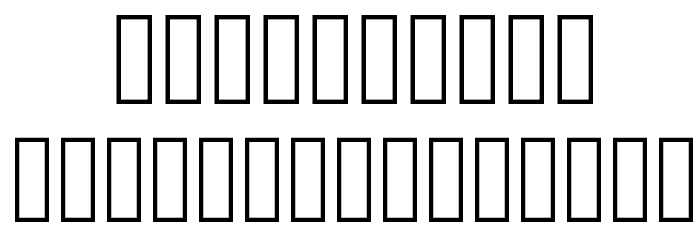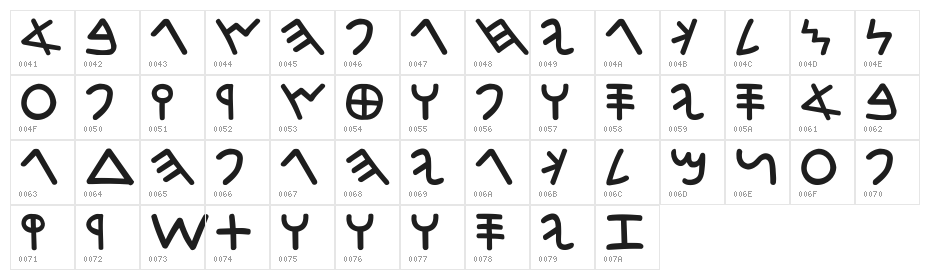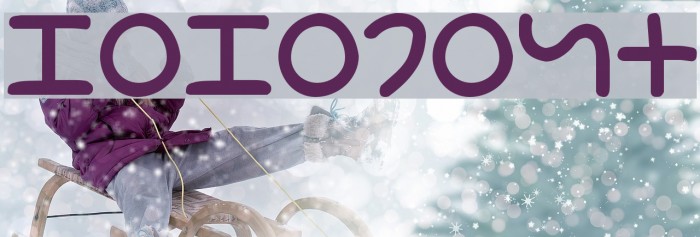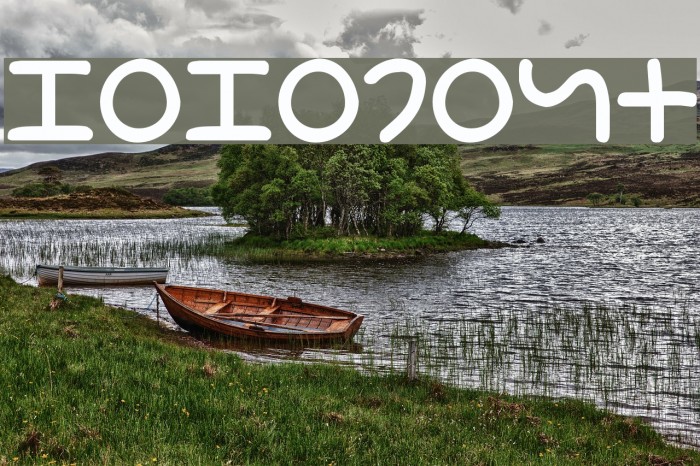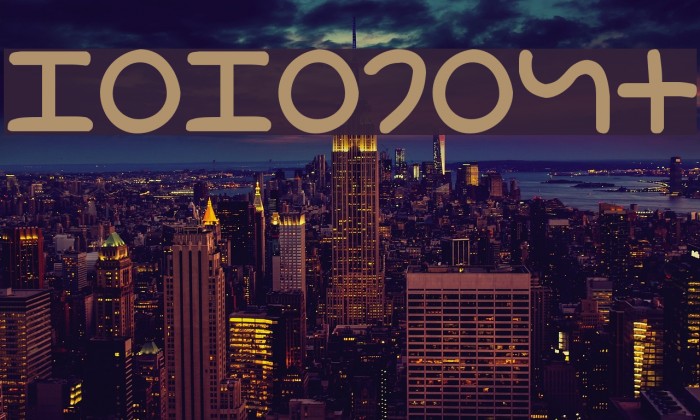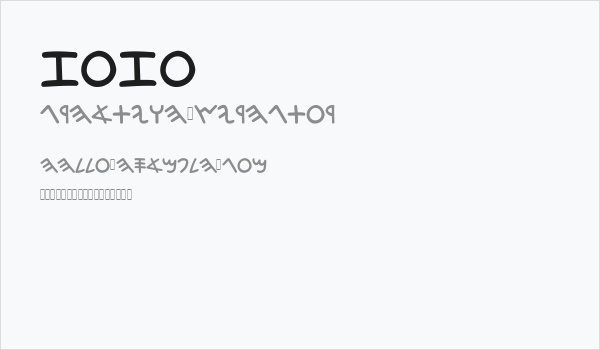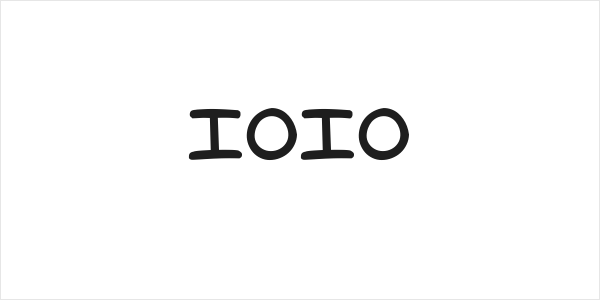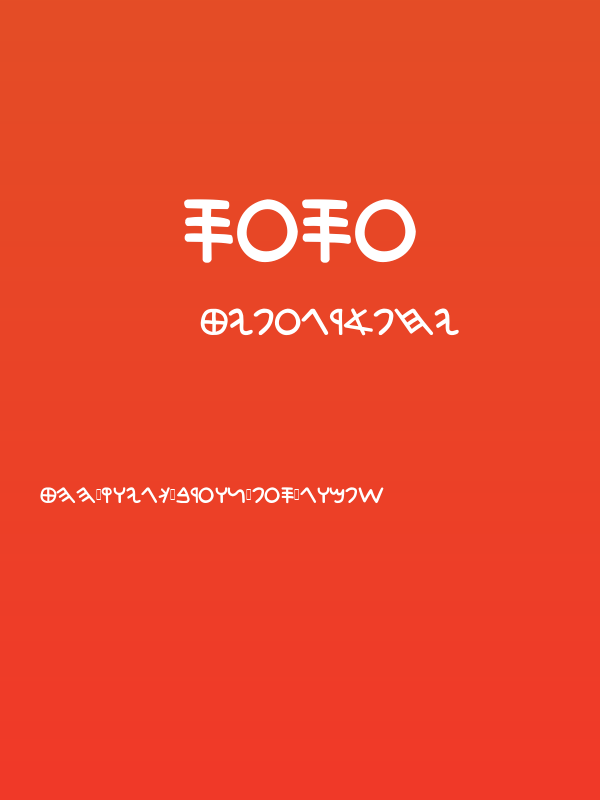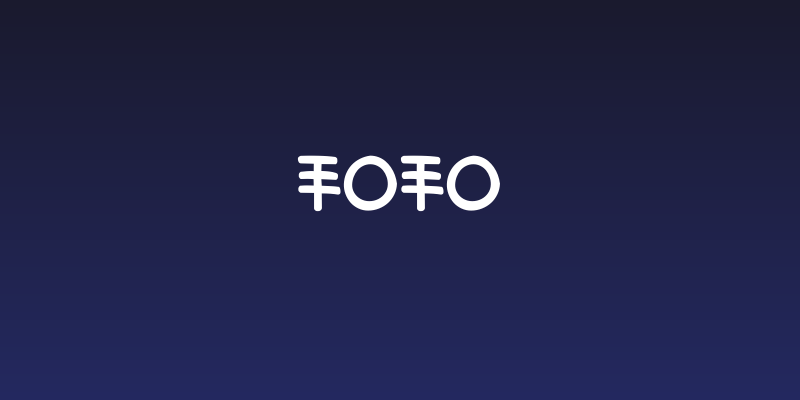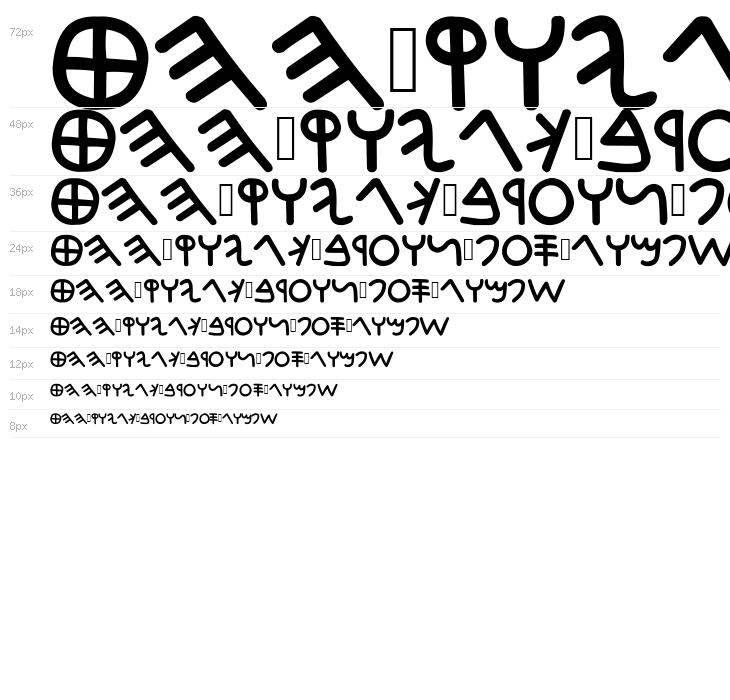
zozo Font
| Cas d'utilisation | Logos, Posters, Creative projects |
| Projets proposés | Ideal for fantasy-themed designs, game interfaces, artistic posters, and unique branding projects. |